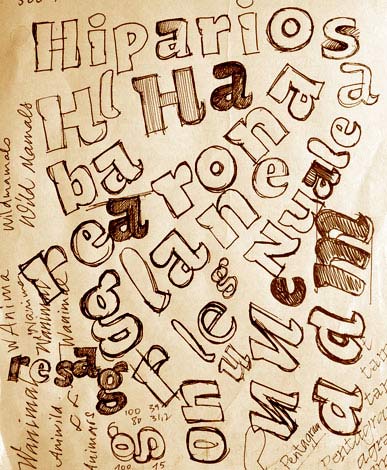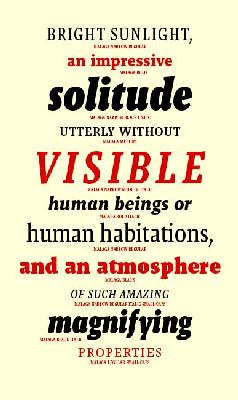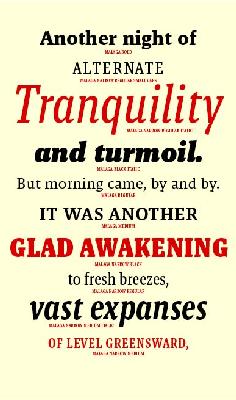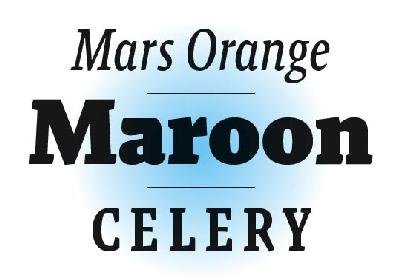
Auch im Fontblog schon präsentiert und kommentiert: die neue Schrift von Xavier Dupré mit dem nach Eis und Sonne klingendem Namen Malaga. Wie schon auf der Typo Berlin angekündigt wird unsere nächste Slanted Ausgabe sich mit dem Thema Antiqua Schriften befassen. Ganz im Zeichen der Neu-Interpretationen... Wie viel ist an dieser Schrift Antiqua, wie viel Serif?
Xavier Dupré was born in 1977 in France. He first studied graphic design in Paris, then calligraphy and typography at Scriptorium de Toulouse. From 1999 to 2001 he worked as a type designer in a packaging design agency in Paris. He has collaborated on Renaissance letterforms with Ladislas Mandel, known for telephone directory typefaces. From 2001 to 2004 he lived in Cambodia where he designed Latin and Khmer typefaces. He was awarded certificates of typographic excellence from the New York Type Directors Club in 2004, 2005 and in 2006 for Vista Sans. (emigre)
> Wie viel ist an dieser Schrift Antiqua, wie viel Serif?
hm, antiqua ist doch serif, oder habe ich da was verpasst? :)
vielleicht sollte man hier fragen „wieviel ist bei dieser schrift antiqua, wie viel sans und wieviel display?“ in den skizzen sind jedenfalls noch nicht so viele serifen an den buchstaben, wie im veröffenlichten font. ich konnte im fontblog auch schon wahre hymnen auf xavier duprés design-output lesen, was einen notorischen skeptiker natürlich aufhorchen lässt.
ich empfinde die malaga in bezug auf das antiqua-motiv ungefähr so, wie die fraktur von underware, bezogen auf das fraktur-motiv: hau noch einen extra schag sahne drauf, und das ganze schmeckt nach besseren zeiten …
schlag sahne ist super, thomas. das triffts.
hat aber wahrscheinlich auch mit geschmacksvorlieben zu tun – wir sind wohl nicht so süss oder wolkig veranlagt? oder sehr selten an der kuchentheke.